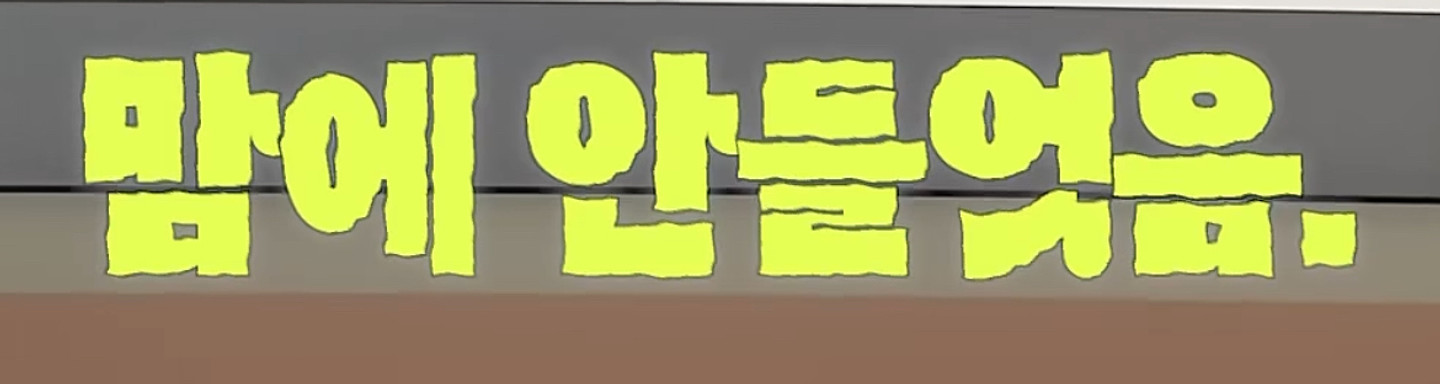
검색해보니 KoreanYASSR Regular 라는 폰트가 나오는데, 막상 찾아보면 조금 다르게 생겼다는 생각이 들어서요 ㅠㅠ 더 많은 분들의 의견이나 답변을 듣고 싶습니다!! 혹시 이 폰트의 이름을 아시는 분이 계신다면 알려 주시면 감사하겠습니다!
교보손글씨 2020 박도연 교보문고
2020년 교보손글씨대회 수상작 "교보손글씨 2020 박도연" 글씨체 입니다.